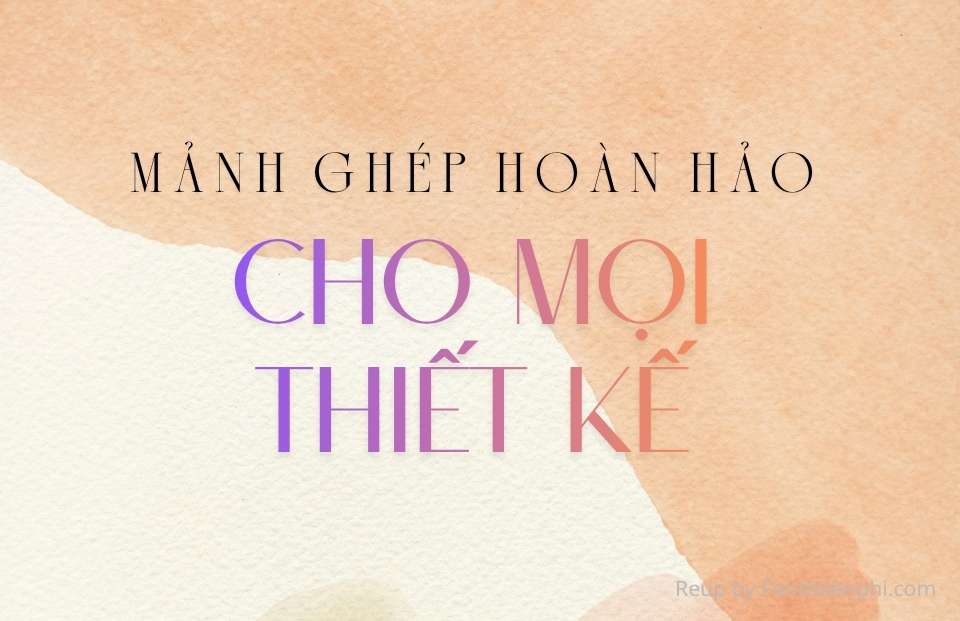
Font Việt Hóa 1FTV VIP Perfect Girl Sans – Mảnh Ghép Hoàn Hảo
Khám Phá Font Việt Hóa 1FTV VIP Perfect Girl Sans – Mảnh Ghép Hoàn Hảo Cho Mọi Thiết Kế
Tại Sao 1FTV VIP Perfect Girl Sans Là Sự Lựa Chọn Đáng Giá?
Không phải ngẫu nhiên mà bộ font này lại được gán nhãn “VIP” và “Perfect”. Dưới góc độ của một người làm thiết kế, phông chữ này mang đến những giá trị sâu sắc vượt xa một công cụ gõ văn bản thông thường.
1. Đường Nét Thiết Kế Mềm Mại, Đầy Cảm Xúc
Đúng như tên gọi Perfect Girl, phông chữ này sở hữu cấu trúc chữ cái cân đối với những đường bo cong nhẹ nhàng, thanh thoát. Không cứng nhắc như các dòng sans-serif truyền thống, bộ font phảng phất nét duyên dáng, lôi cuốn nhưng vẫn giữ được sự mạnh mẽ, gọn gàng của nhịp sống hiện đại. Sự chuyển đổi tinh tế giữa các nét chữ tạo ra một nhịp điệu thị giác êm ái, giúp thổi hồn vào mọi ấn phẩm.
2. Dấu Tiếng Việt (Việt Hóa) Chuẩn Mực, Tỉ Mỉ Font Việt Hóa 1FTV VIP Perfect Girl Sans
Điểm sáng giá nhất của phiên bản này chính là chất lượng Việt hóa đến từ đội ngũ 1FTV. Font Miễn Phí đánh giá rất cao sự chăm chút trong từng bộ dấu:
• Các dấu ngã, dấu hỏi, dấu nặng được đặt ở tỷ lệ vàng so với phom chữ gốc.
• Khoảng cách (kerning) giữa các ký tự có dấu được tinh chỉnh hoàn hảo, triệt tiêu hoàn toàn tình trạng “lệch dấu” hay rối mắt khi gõ các đoạn văn bản dài.
3. Khả Năng Ứng Dụng “Đa Hệ” Trong Thiết Kế
Một phông chữ xuất sắc là phông chữ có tính ứng dụng cao. 1FTV VIP Perfect Girl Sans đáp ứng trọn vẹn tiêu chí đó:
• Branding (Nhận diện thương hiệu): Cực kỳ phù hợp cho logo, bao bì của các thương hiệu mỹ phẩm, thời trang cao cấp, spa hay trang sức.
• Editorial & Social Media: Làm tiêu đề (Headline) ấn tượng cho tạp chí nghệ thuật, quote truyền cảm hứng hoặc banner quảng cáo mạng xã hội.
• Typography: Hoàn hảo cho các ấn phẩm mang tính cá nhân hóa cao như thiệp cưới, lookbook ảnh.
Thông Tin Chi Tiết Về Bộ Font Việt Hóa 1FTV VIP Perfect Girl Sans
Tên Font 1FTV VIP Perfect Girl Sans
Phong cách Sans-Serif (Không chân), Hiện đại, Thanh lịch
Tình trạng Việt hóa Hoàn thiện 100%, Kerning chuẩn xác